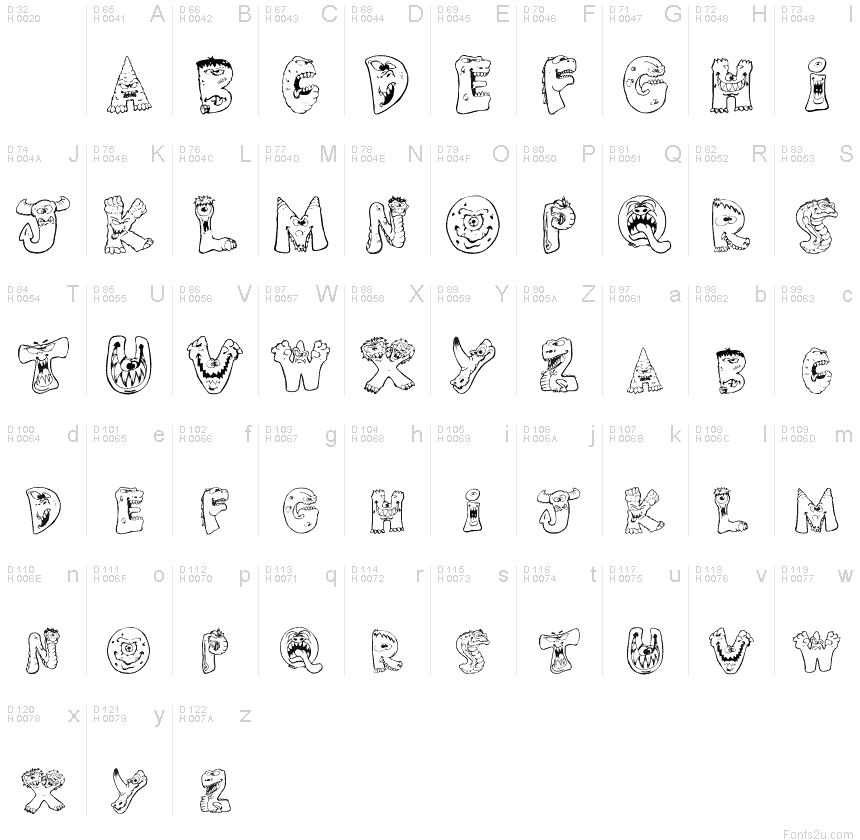
Scary Monsters di Melle Derieppe Claude è un font cartoon gratuito dallo spirito giocoso tipico dei B-movie. Le lettere trasformano l'alfabeto in tante creature: una S che è un serpente attorcigliato, una C che morde, una A irregolare piena di zanne, una R pelosa con un occhio solo e una Y dal muso lungo. Il tutto disegnato con contorni tremolanti, occhi sporgenti, artigli e denti esagerati.
È perfetta per volantini di feste di Halloween, copertine di fumetti, poster spaventosi per bambini, packaging originali e titoli in cui il font può far ridere da solo. Usalo per parole brevi, monogrammi o capilettera quando vuoi che le lettere stesse sembrino i mostri, invece di limitarsi a scriverne il nome.